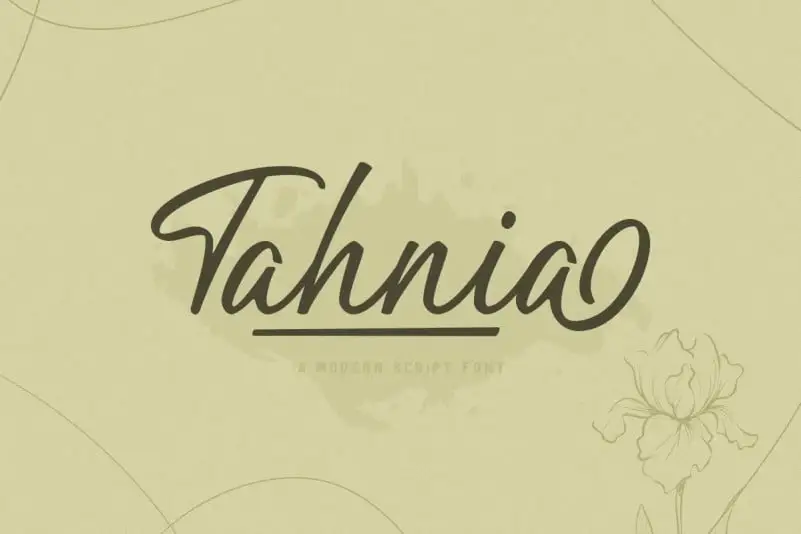
Tahnia Script Font – Fonte Grátis
Tahnia Script Font
Tahnia Script é uma fonte de escrita manuscrita que foi criada por Rillatype com um estilo distintivo de traço assinado. Esta elegante fonte moderna oferece um toque natural da escrita manual, repleta de alternativas para atender a uma variedade de necessidades gráficas. Ideal tanto para headlines quanto para logotipos, citações, roupas, convites, marcação, embalagens e anúncios, esta fonte tem tudo o que você precisa para criar um design envolvente. Para adicionar sublinhados, basta digitar _ seguido de um número entre 1 e 3, por exemplo: _1 ou _2 ou _3. Tahnia Script é perfeita para designers em busca de uma fonte única que ofereça um toque natural e sofisticado.